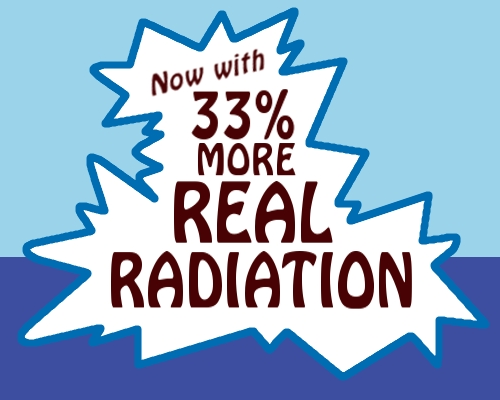
Polices de Caractères
Team Fortress 2 fait appel à une variété de polices de caractères pour ses marque et ses promotion.
Polices
Polices d'interface utilisateur
Les polices d'interface utilisateur sont fournies avec le jeu et sont stockés dans /team fortress 2/tf/resource.
| TF2 | |
Ceci est la police toutes en majuscules, mince, comme des arrêtes. Disponible sur DaFont. Télécharger |
| TF2 Secondary | |
Ceci est la police majuscules et minuscules, petite, mince et arrondie. Disponible sur DaFont. Télécharger |
| TF2 Build | |
Ceci est la police toutes en majuscules. Disponible sur DaFont. Télécharger |
| TF2 Professor | |
Ceci est la police de la craie utilisés pour les textes du MOTD (Message du jour). Disponible sur DaFont. Télécharger |
Les polices en jeu
Les polices utilisées sur les textures du jeu.
| Aachen Bold | |
Cette police est utilisée pour les logos de Casali Shafting Co. et de Husky Acres. Police commerciale. Acheter (39.96$) |
| Baskerville | |
Cette police est utilisée pour certains des mots sur le Bonk! Atomic Punch RED. Police commerciale. Acheter (24.80$) |
| Carnova Narrow | |
Cette police est utilisée pour les signalisations du jeu (tels que ceux désignant un Points de contrôle). Police commerciale. Acheter (12$) |
| Hobo Std | |
C'est la police utilisée pour certaines formulations des canettes de soda comme le Bonk! Atomic Punch et le Crit-a-Cola. Police commerciale. Acheter (24.75$) |
| Impact | |
Police utilisée pour le logo de General Industries Co. et la banderole de la Mise à jour de l'Engineer. Police livrée avec Microsoft Windows et Apple Mac OS X. |
Marques externes
En dehors du jeu, TF2 possède d'autres polices qui sont utilisées pour les marques :
| Amarillo USAF | |
Police utilisée pour le titre du journal Commando du Soldier. Police libre. Télécharger |
| Arial Black | |
Police utilisée pour le logo de TF Industries. Police livrée avec Microsoft Windows et Apple Mac OS X. |
| Astro City | |
Police utilisée pour le texte principal des bandes dessinées. Police commerciale. Acheter (199$) |
| Bebas | |
Police utilisée pour le logo Mann Co.. Police libre. Télécharger |
| Boris Black Bloxx | | ||
| Blackoak | |
C'est la police utilisée pour les gros titres des mises à jour majeures. Livrée avec Adobe Photoshop depuis la version CS3. Police commerciale. Acheter (29$) |
| Brush Script STD | |
C'est la police utilisée pour la signature de Saxton Hale. Il est aussi la police utilisée sur le Marchand de Sable et sa balle. Police commerciale. Acheter (35$) |
| Cat Women | |
Police utilisée pour la page de mise à jour Scream Fortress. Police libre. Télécharger |